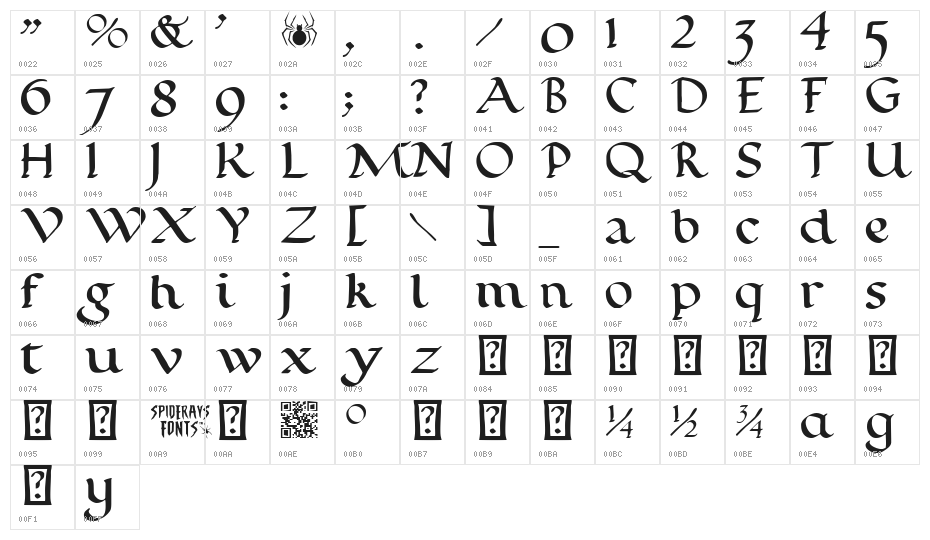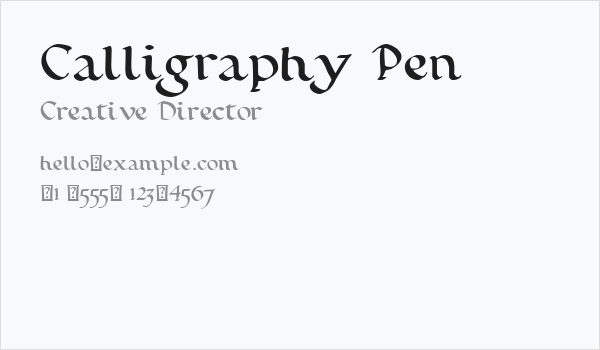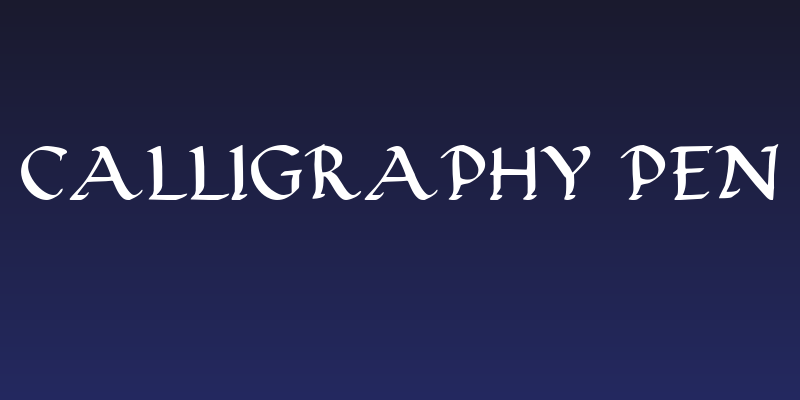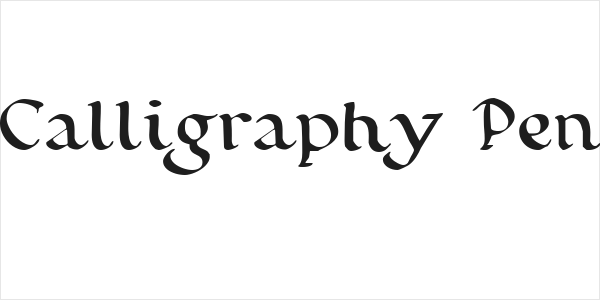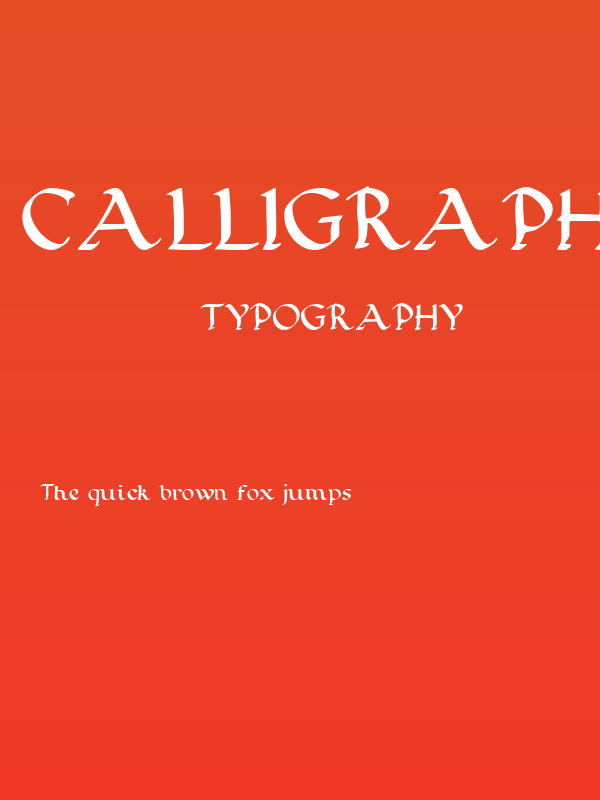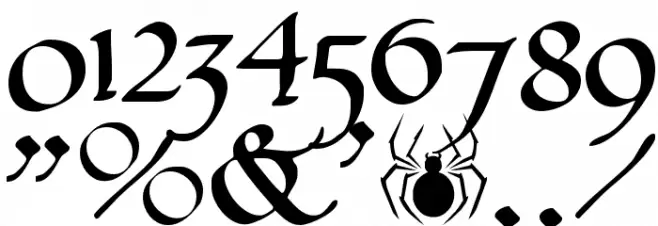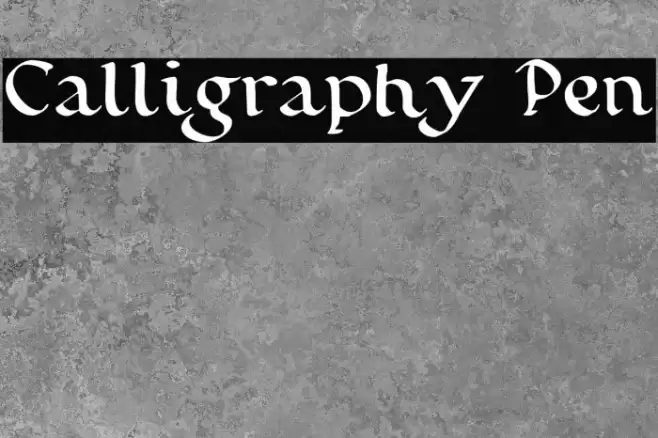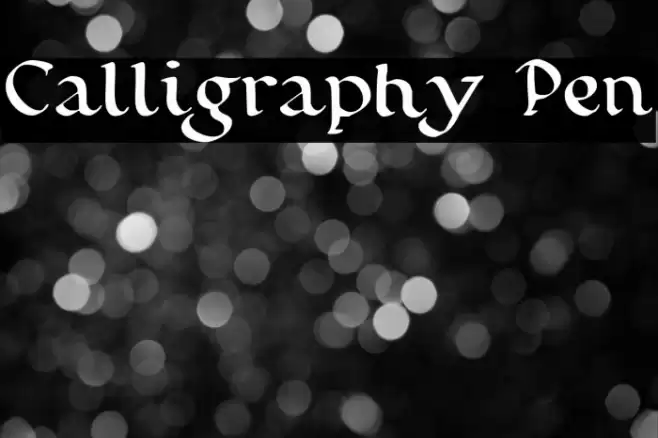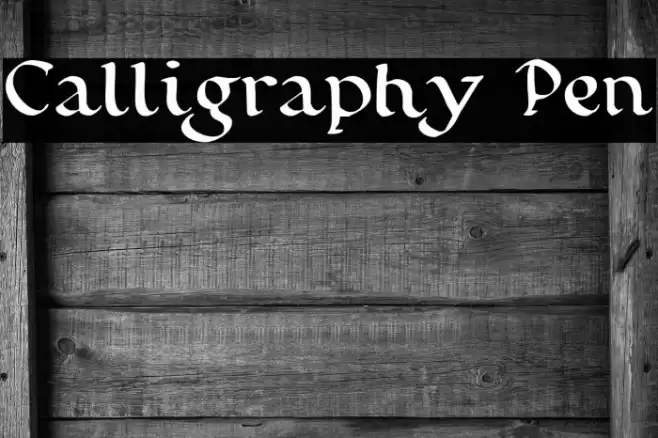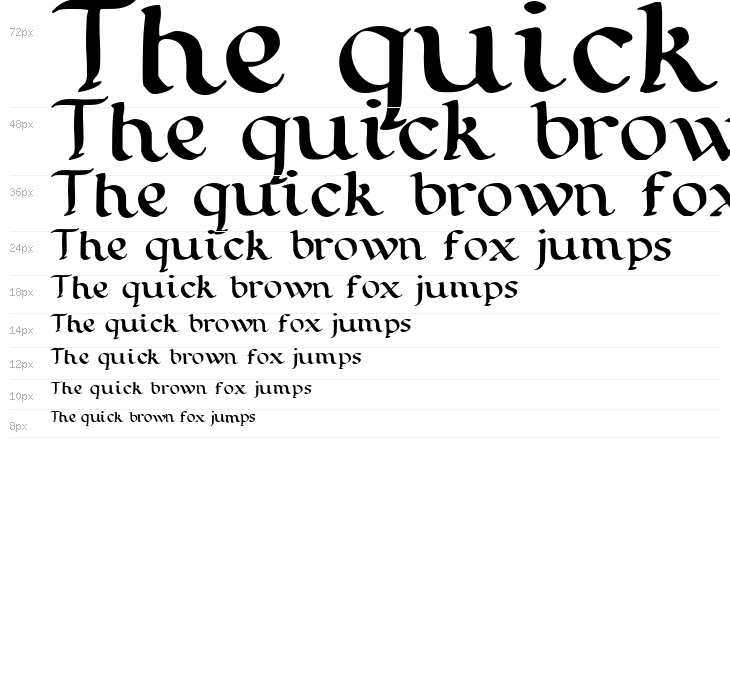
Calligraphy Pen Font
✎ Calligraphic
| Gesamtstil | Classic |
| Anwendungsfall | Headlines, Invitations, Certificates |
| Vorgeschlagene Projekte | Ideal for wedding invitations, formal event programs, certificates, and branding materials that require a traditional and elegant touch. |